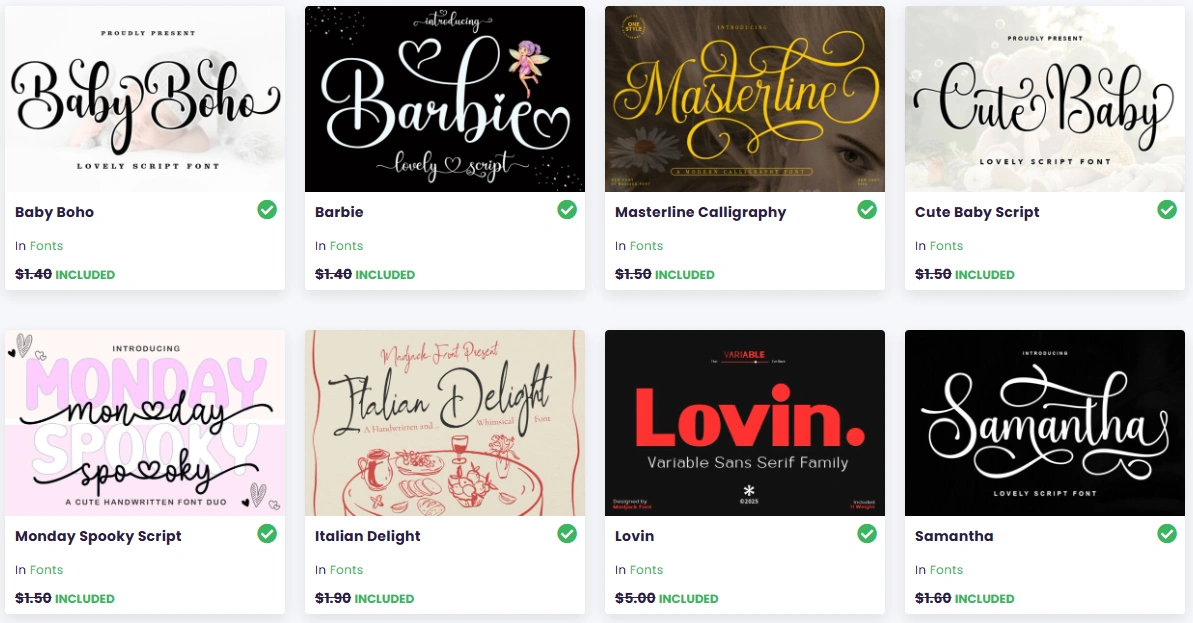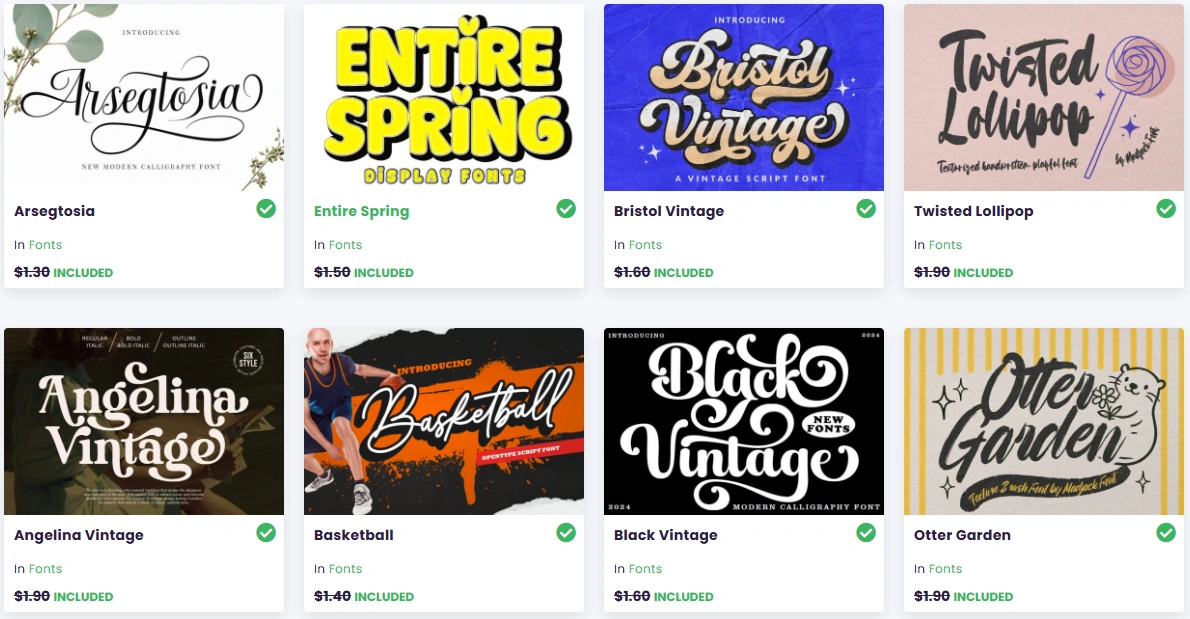
免費英文字體包下載 Mega Collection Font Bundle
做網站、寫 Blog、經營品牌久了以後,你應該會發現字體其實是很容易被低估的細節,但它卻直接影響讀者對你內容的第一印象。剛好最近發現 Creative Fabrica 又有限時免費活動啦,送免費字體包「Mega Collection Font Bundle」,收錄 58 款字體,有手寫、書法、復古與展示用途,原價要 946 美元,現在按一個按鈕就能免費領取。活動只剩不到三天就會結束,有需要的話就要抓緊時間下載啦。
字體包裡有什麼?
這個字體包總共收錄 58 款字體,全部出自設計師 madjack.font,風格集中在手寫體 (Script & Handwritten)、書法體 (Calligraphy)、復古襯線 (Vintage Serif) 以及展示用無襯線字體 (Display / Sans Serif) 這幾類。
比較有代表性的幾款包括 Baby Boho、Masterline Calligraphy、Cute Baby Script、Italian Delight、Angelin Calligraphy、Bristol Vintage、Angelina Vintage,還有帶點趣味風格的 Twisted Lollipop 和 Basketball 等,單款原價大約落在 1.3 美元到 5 美元之間。
整體來看,這批字體特別適合用在品牌命名、婚禮相關設計、手作商品標籤、社群圖文標題,或是需要營造柔和、溫暖、復古氛圍的視覺專案上。如果你的內容偏向生活風、手作風或是走溫馨路線,這個字體包應該會很適合。